Chọn font phù hợp?
Thế nào là chọn font phù hợp? Làm sao để bức hình hài hòa, trông đẹp mắt và không mắc lỗi về font chữ?
Sau quá trình tìm stock, tải font, ... chúng ta đã có thể bắt tay vào design rồi. Với những bạn mới bắt đầu học thiết kế bìa truyện, quotes các thứ thì khâu xử lý hình ảnh nên làm đơn giản hết sức có thể. Mà với kinh nghiệm rất ít ỏi thì việc cắt ghép, chỉnh sửa hình cũng hơi khó khăn, chúng ta nên chọn những hình dễ design như bài trước mình đã đăng để đi thẳng tới bước chèn text luôn rồi chỉnh hiệu ứng ảnh.
(Ở đây mình xin phép chỉ nói riêng đến bìa truyện thôi vì quotes, ava và banner không phải là sở trường của mình.)
Text trên hình thì quan trọng nhất là khâu chọn font, sau đó mới là màu sắc, kích cỡ và hiệu ứng (nếu cần). Một font chữ phù hợp dựa vào rất nhiều yếu tố: text dùng font đó có vai trò gì trong hình (chính hay phụ?), thể loại truyện mà bạn đang des là gì và phụ thuộc vào cả những chi tiết trong hình nữa.
Như mình đã nói ở bài trước thì font cứng thường được dùng làm text phụ và tên tác giả, font mềm bay bướm cầu kỳ thì thường được dùng làm text chính, tên truyện và những phần quan trọng. Tất nhiên là mỗi người có một kiểu cách des khác nhau và mắt thẩm mỹ khác nhau, không phải ai cũng theo cái quy luật cứng nhắc đó. Nhưng chúng ta vẫn phải biết những kiến thức cơ bản để sản phẩm mình làm ra được đẹp.
Hãy nhìn hình dưới đây:
(Quá khứ dữ dội của mình đấy)
Hình trên nó không đẹp chút nào, và chính xác là như vậy đó ạ.
Font mềm là những font rất nổi và chỉ được dùng trong text chính, nhất là hình này lại có nhiều họa tiết, việc dùng font mềm làm text phụ là điều tối kị nhất, chưa kể đến màu sắc và kích cỡ quá mức cho một bìa cổ trang. Khoảng cách giữa các dòng quá lớn nữa, nhìn khoảng bìa đó rối tung hết cả lên rồi.
Vậy hình này thì sao?
Bìa của chị Sương Ômêga - một tiền bối trong lĩnh vực design mà mình rất ngưỡng mộ.
Bìa trên chị ấy làm cũng dùng font mềm, lại còn là Hand writing cho text phụ nhưng bức hình không hề bị rối. Phần chèn text phụ là cả một khoảng trống, hơn nữa cả text chính lẫn tên tác giả đều đã dùng font cứng rồi nên lựa chọn font mềm cho text phụ có lẽ cũng là để trung hòa, để tổng thể bìa không bị cứng ngắc.
Mình nghĩ tấm dưới đây của mình cũng tương tự như vậy:
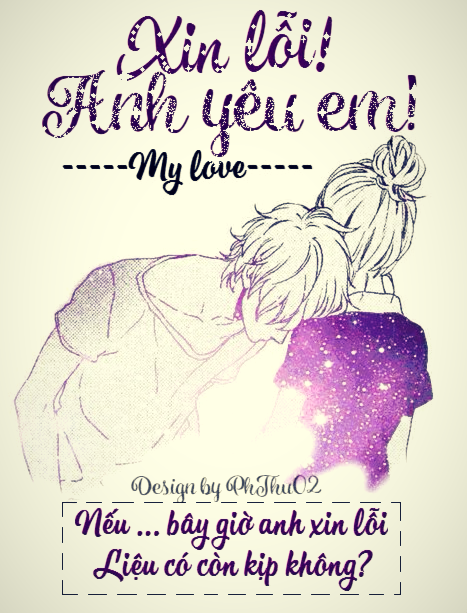
Mặc dù bìa này đầy khuyết điểm: hình vẫn còn bị tối, text phụ, tên tác giả và cả cái cre cũng quá to nhưng mình nghĩ chọn font text phụ cùng font với tên tác giả không phải là không hợp lý.
Thật ra design rất linh hoạt, bạn hoàn toàn có thể thay đổi và sáng tạo dựa theo khả năng của bạn. Nhưng nếu mới bắt đầu tập tành trên wattpad thì bạn nên tuân theo những quy tắc cơ bản để có một tấm bìa đẹp và dễ nhìn.
Thật ra nếu các bạn để ý sẽ thấy từ trước tới giờ mình toàn dùng font cứng cho text phụ và tên tác giả, rất hiếm khi mình dùng font mềm. Nhưng vì số lượng ảnh được đăng chỉ có hạn nên mình sẽ không trưng ra đây đâu :v
Còn text chính thì thường không dựa vào vai trò của nó trong bìa mà thường dựa vào thể loại truyện và một vài yếu tố khác. Ở bài này mình sẽ nhấn mạnh đến yếu tố thể loại truyện. Cơ bản là:
- Truyện bay bổng, lãng mạn thì hợp với font mềm mại, uốn lượn.
- Truyện thanh xuân vườn trường thì hợp với những font mềm đơn giản, bay bướm hoặc font Hand writing...
- Truyện buồn, u tối, bí ẩn hay hành động thì hợp với font cứng, dày hoặc brush mỏng và thẳng.
Credit: Hãy nhắm mắt khi anh đến.
- Truyện kinh dị thì hợp với những font brush xù xì, hiệu ứng máu chảy hoặc font cứng pha script nhưng cũng có chút xù lên:
Credit: Pinterest.
- Truyện cổ trang thì hợp với font thư pháp hoài cổ.
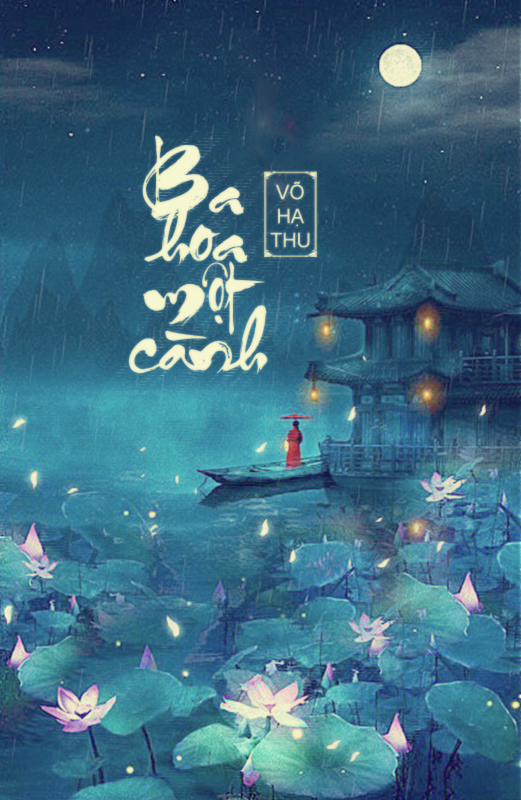
Credit: Huaban.
Trên đó là những kiểu truyện và font phù hợp quen thuộc, tuy nhiên không phải thể loại nào cũng vậy. Làm bìa kinh dị không nhất thiết phải dùng font máu me, bìa cổ trang không nhất thiết phải dùng font thư pháp nếu không sẽ bị nhàm và thành lạm dụng.
Các bạn hoàn toàn có thể thử với những kiểu font khác mà không làm mất đi cái chủ đề của truyện, ví dụ:
Credit: Huaban.
Font thư pháp không phải lúc nào cũng hợp với bìa cổ trang, đôi khi những font cứng pha trộn với sự uốn lượn của script cũng là một sự lựa chọn hoàn hảo.
Hay những font viết tay mềm mại như thế này:
Credit: Huaban.
Thật sự thì mình rất thích sử dụng font Hand writing cho bìa cổ trang. Có điều mình cũng thuộc dạng hay dùng thư pháp, font Hand writing đẹp lại không dễ kiếm nên ít khi xài lắm. Các designer mới vào nghề nếu đã quá quen với thư pháp thì hãy thử đổi gió bằng font Hand writing khi des cổ trang xem sao :v
Truyện kinh dị thì hợp với font brush máu me, nhưng nếu là kinh dị pha trộn với các thể loại khác thì bạn hoàn toàn có thể sử dụng font mềm, hoặc là font kiểu "con lai" như dưới đây:
(Bìa của chị Sương Ômêga)
Thật sự thì với kiến thức ít ỏi, mình cũng không rõ font text chính trên hình là script, brush hay hand writing nữa. Nhưng thật sự thì nó rất hợp với bìa, kiểu dáng mềm mại tròn tròn lại vừa có một chút xù xì kinh dị.
Lý thuyết chỉ là một phần, cái quan trọng nhất là phải luyện tập nhiều thì tay nghề sẽ được nâng cao. Bản thân mình lúc mới học des cũng lao đao lắm, khoản chọn font thì còn đỡ đỡ chút chứ cỡ chữ với màu sắc thì tệ hại thôi rồi. Bài sau mình sẽ đăng về khoản đó nha.
Tổng kết lại, chúng ta có ba điều sau cần ghi nhớ với những designer mới vào nghề:
- Tên tác giả và text phụ nên dùng font cứng, hạn chế dùng font mềm.
- Chọn font phù hợp với thể loại truyện và hình.
- Không sử dụng quá nhiều font trong một hình.